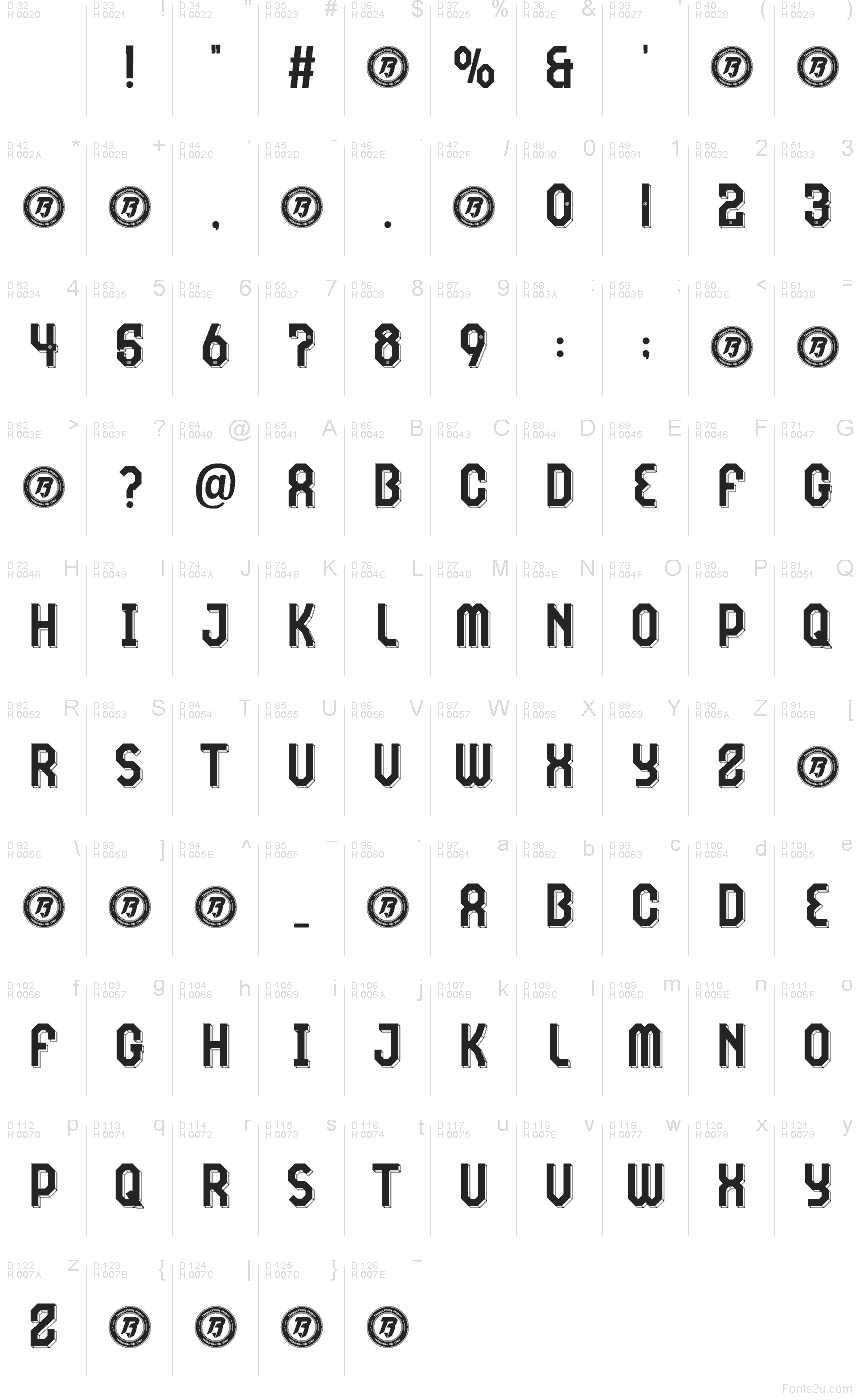
Feijenoord Personal Use 5 de Trequartista Studio es una tipografía display 3D gratuita con el estilo contundente de las letras de los juegos arcade retro. Las mayúsculas parecen talladas en metal biselado, con esquinas marcadas, cortes achaflanados y un efecto de línea sombreada que otorga a las letras una presencia sólida, digna de un título de videojuego.
Es ideal para titulares de carteles, branding de esports, portadas de álbumes, tarjetas de título y gráficos estilo jersey, donde las palabras cortas necesitan ese aspecto anguloso y estructurado. Al ser gratuita, también es una gran opción para logotipos, monogramas y frases de portada, ya que la profundidad de sus capas aporta carácter incluso a unas pocas letras.
Feijenoord Personal Use 5 — Presentación de la fuente
Feijenoord Personal Use 5